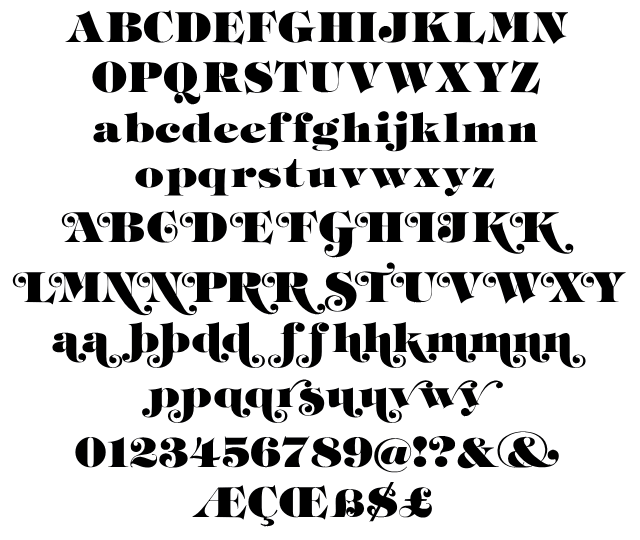
Tiffany Heavy with Swash
bin auf der Suche nach einem seltenen Schriftsatz, namens Tiffany Heavy mit Swashes
Habe überall gesucht und festgestellt dass die Glyphen die ich gerne hätte nur in ein alten Version integriert waren.